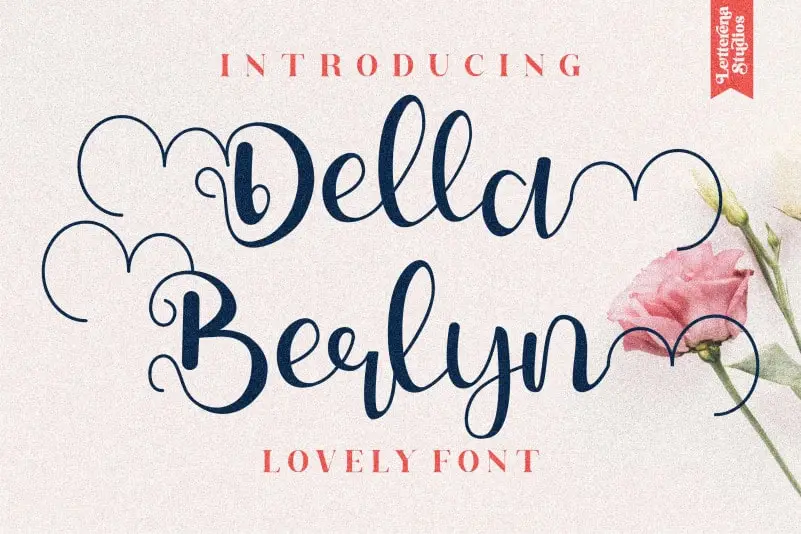
Della Berlyn Calligraphy Font – Fonte Grátis
Della Berlyn Calligraphy Font
A Della Berlyn Calligraphy Font é uma elegante e encantadora fonte de script que se destaca por sua delicadeza e romantismo. Perfeita para designers que buscam um toque especial em cartões de convidado, cartões de agradecimento, mensagens pessoais, logotipos e cartões de visita. Suas linhas fluidas e deslizantes proporcionam uma aparência sofisticada e requintada, enquanto seus detalhes exuberantes e alternativas memoráveis garantem um resultado único e impactante em qualquer projeto design. Perfeito para aqueles que buscam incorporar a autêntica mão escrita em suas criações visuais, seja em cartões de aniversário ou em designs empresariais sofisticados. Feito para os amantes do belo gráfico e dos designers de moda, esta fonte atinge o ponto ideal entre elegância e charme. Seja você um designer de casamento, de logotipos ou mesmo um criador de conteúdo pessoal, a Della Berlyn Calligraphy Font está aqui para adicionar aquele toque especial que torna suas criações únicas e memoráveis.